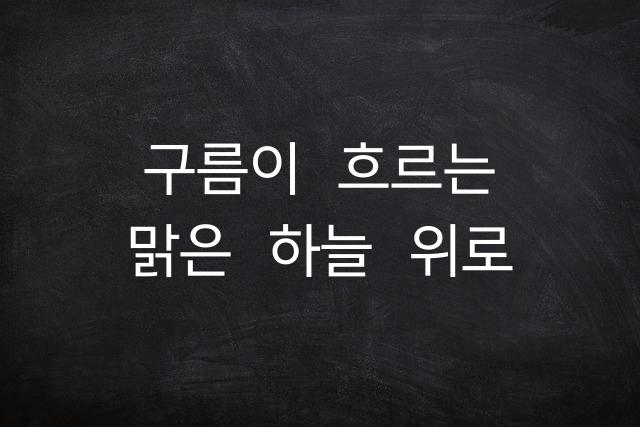
구름 산스는 문서 작성에 최적화된 폰트로, 읽기 쉬우면서도 디자인적인 세련미를 갖추고 있습니다. 편안한 구름처럼 부드럽고 맑은 느낌을 전달합니다.
구름 산스은(는)
두꺼운 스타일, 감성적인, 자연감성, 부드러움, 복실복실 계열의 생김새를 가지고 있으며
웹/앱 디자인, 프레젠테이션, 보고서/문서 등에서 자주 활용되며, 효과적인 메시지 전달에 적합합니다.
이 폰트는 기술/IT, 공공/정부, 금융/비즈니스 분야에 잘 어울리며,
명확한, 전문적인, 단순한 느낌을 담고 있는 것이 특징입니다.
이 폰트와 유사한 폰트로는 나눔 고딕, 스포카 한 산스, 맑은 고딕 등이 있어요. 함께 비교해 보시면 좋습니다!